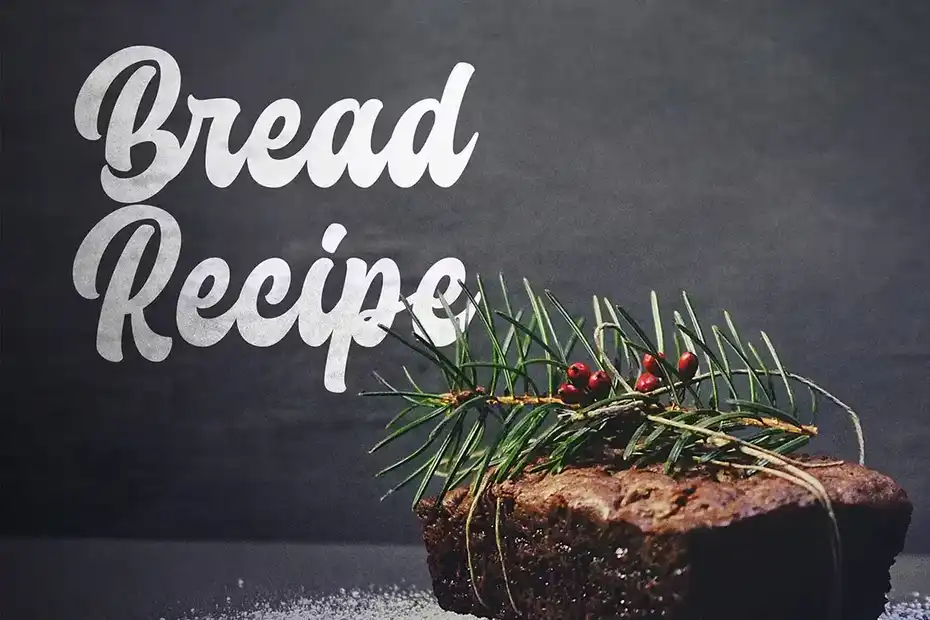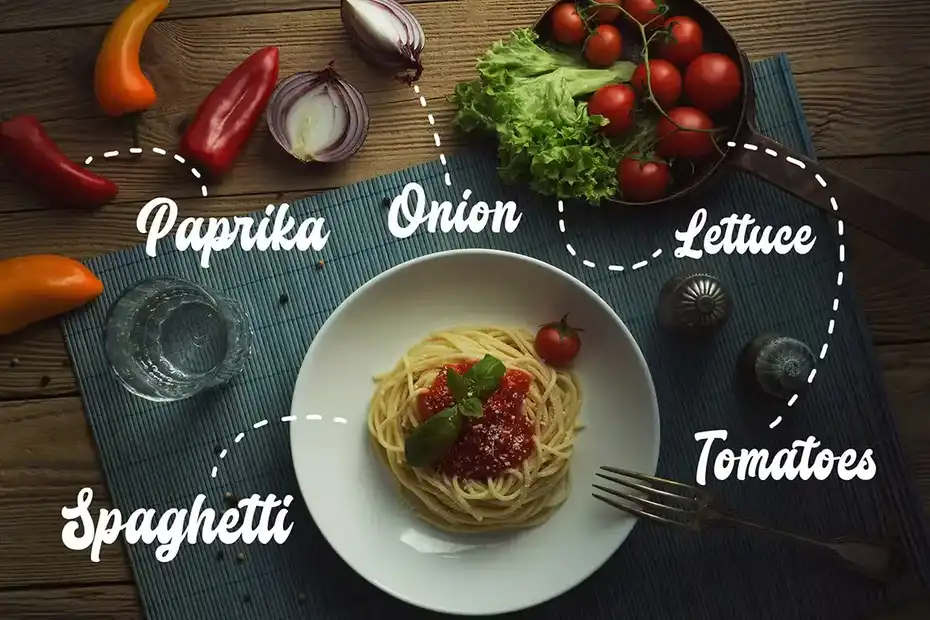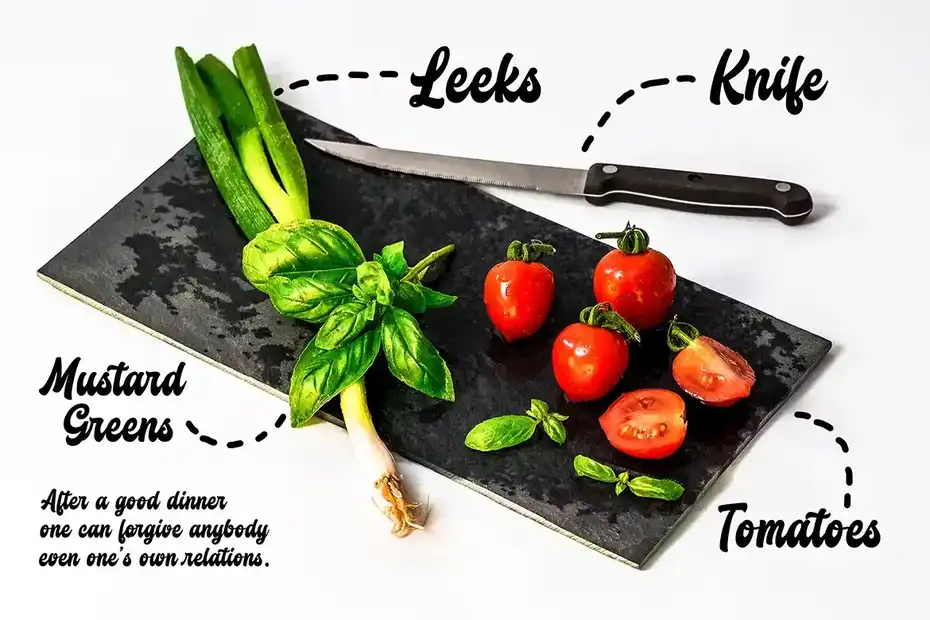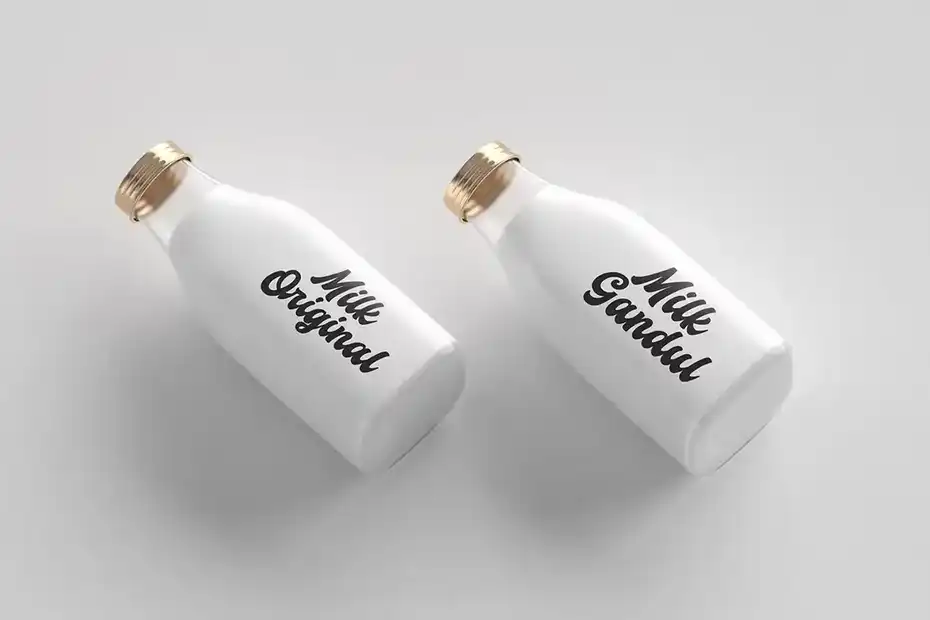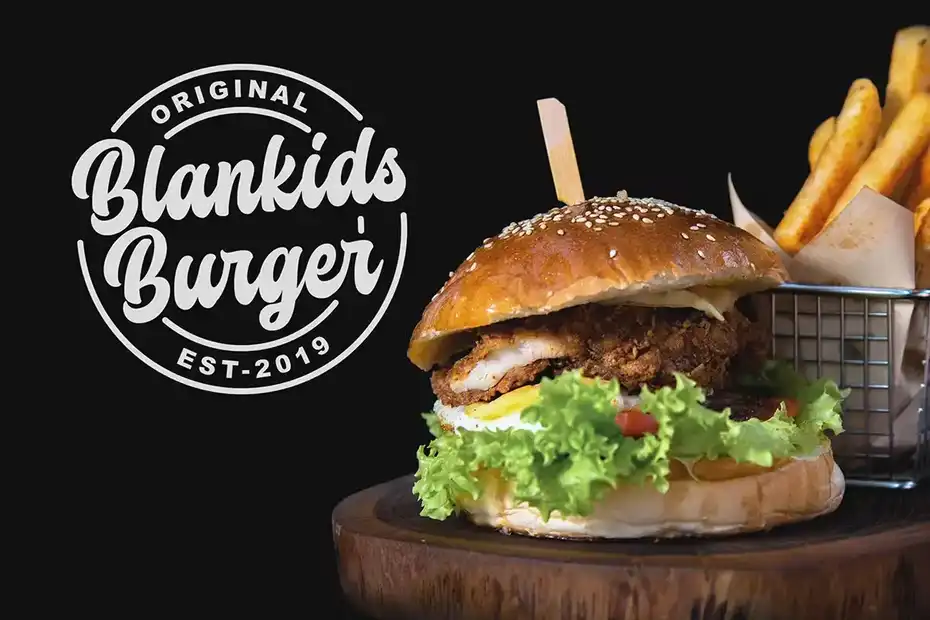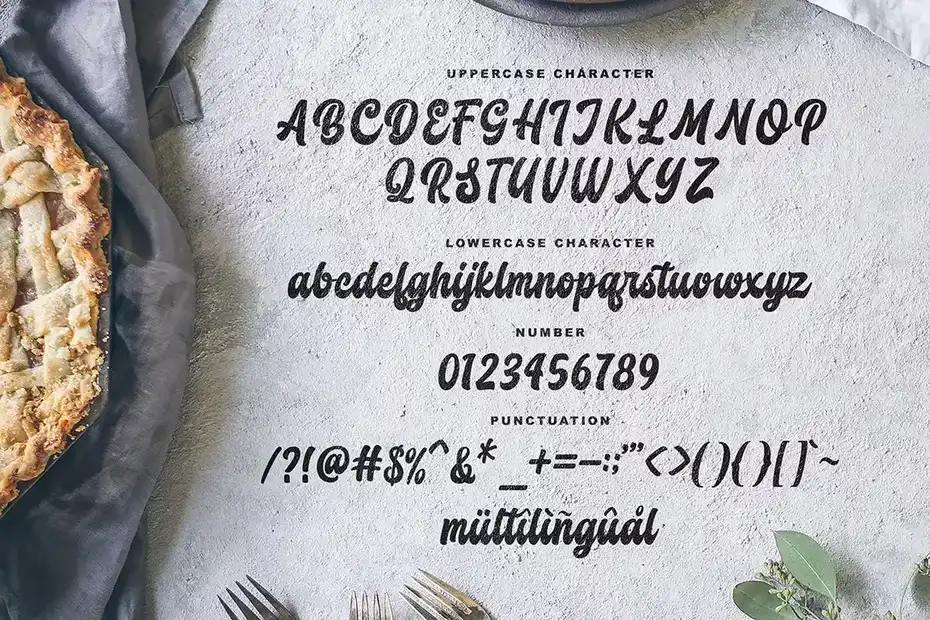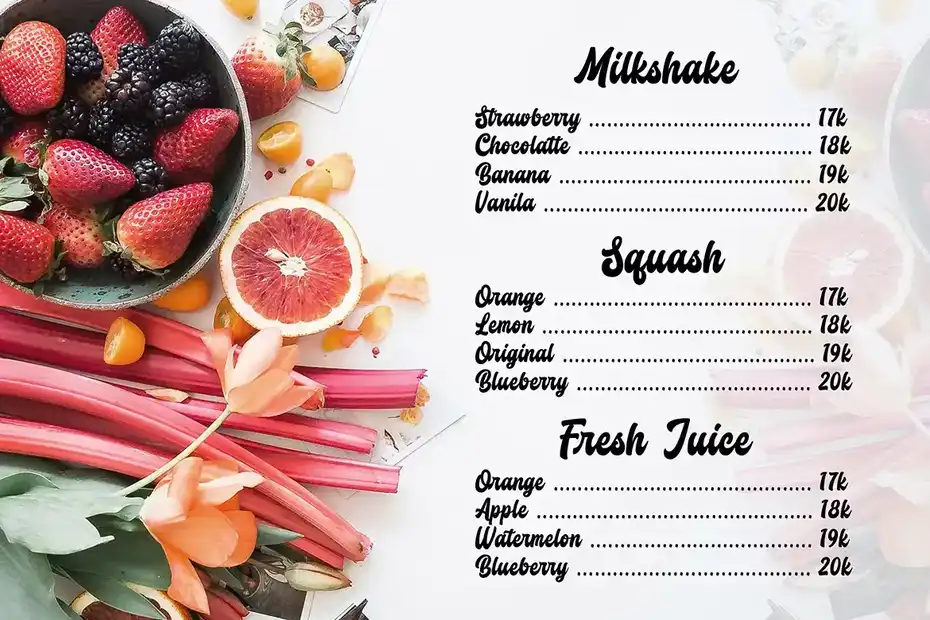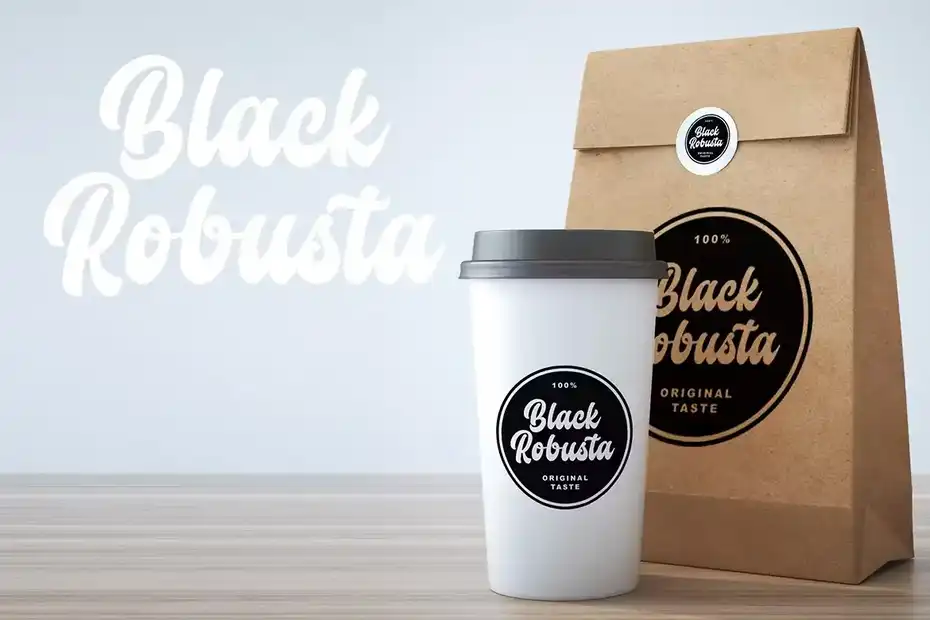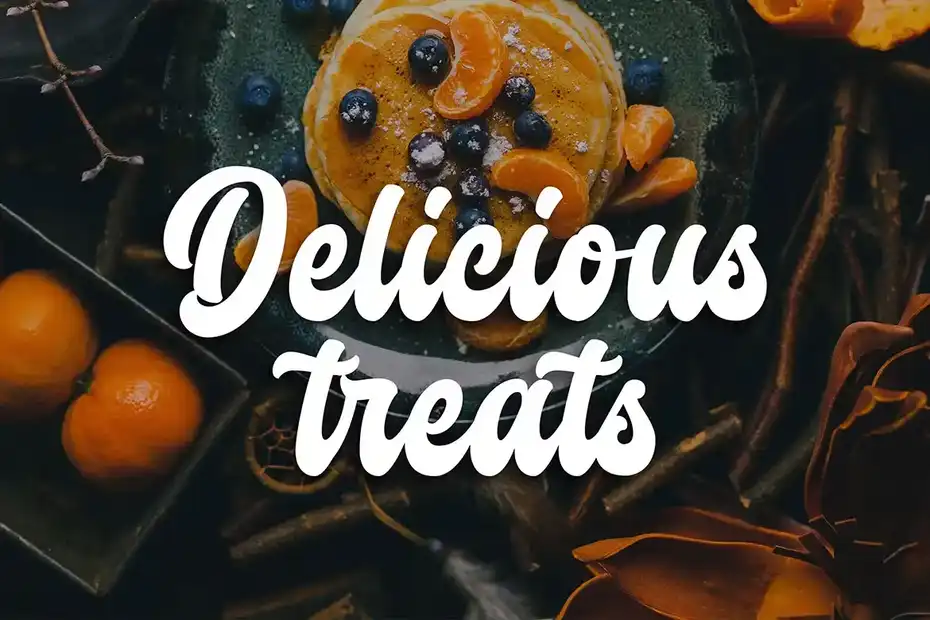
فونت انگلیسی دست نویس Butchery – Bold Script Font : این مجموعه شامل یک فونت انگلیسی دست نویس است که برای لوگوتایپ، پوستر غذا، منو غذا، بسته بندی مواد غذایی و غیره مناسب میباشد.